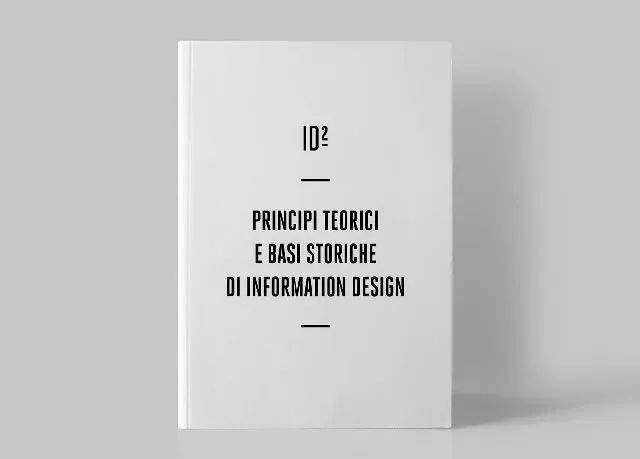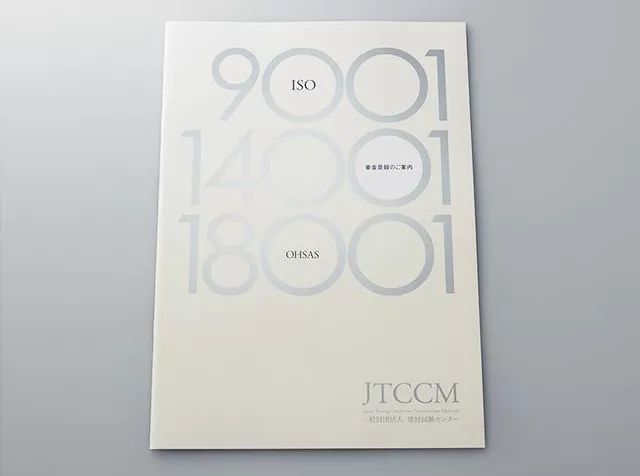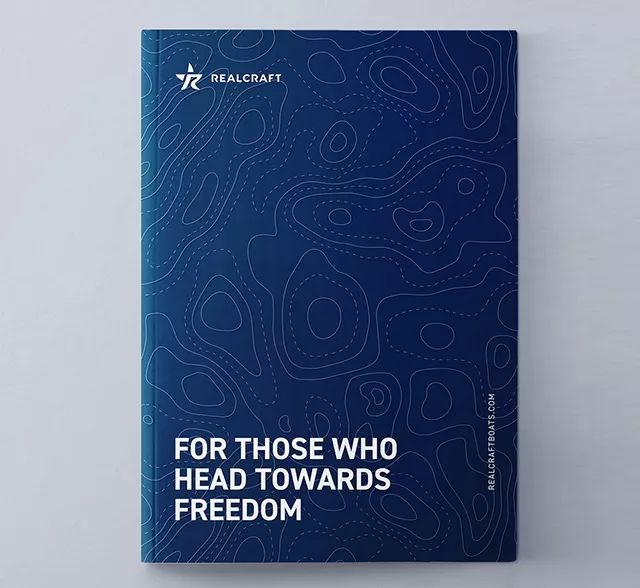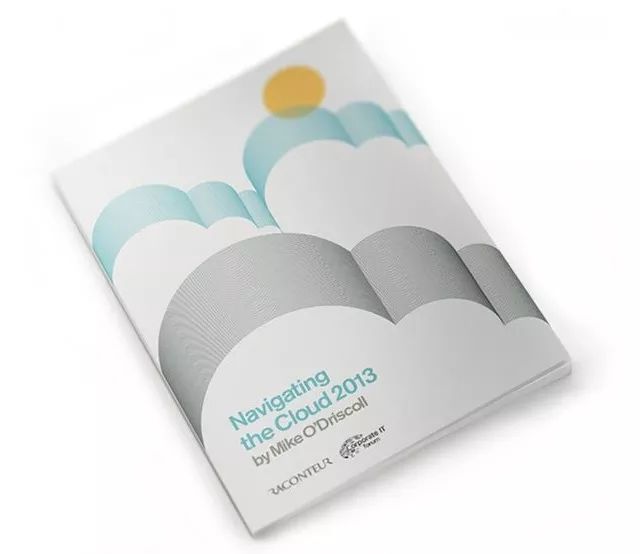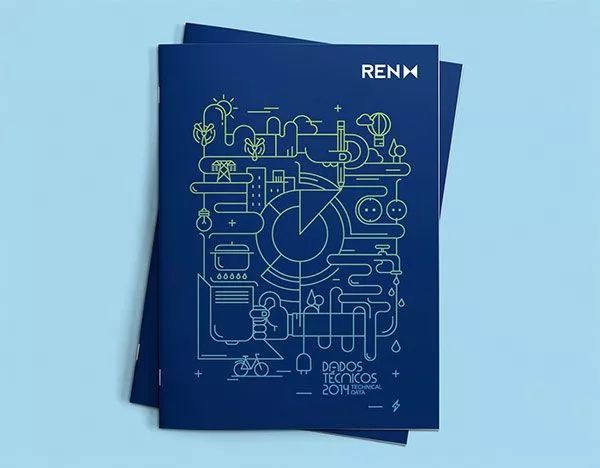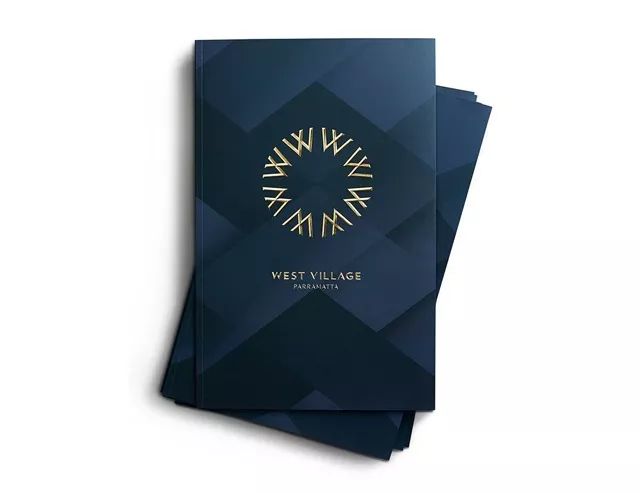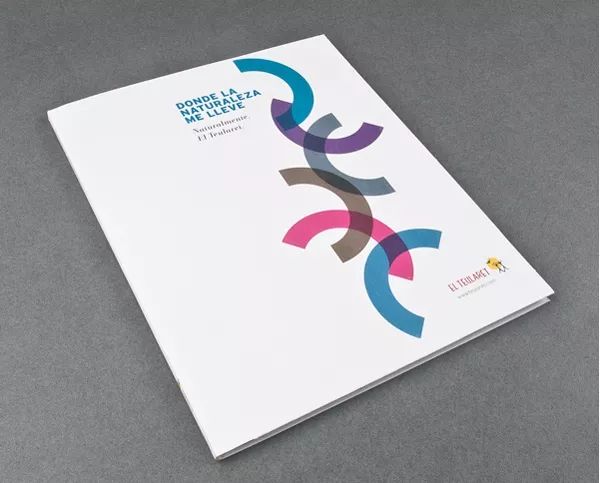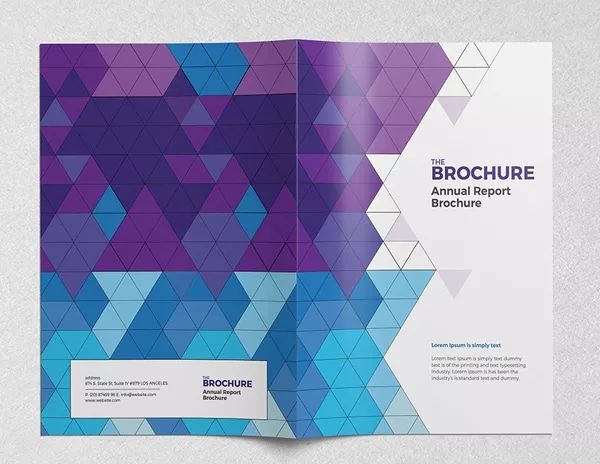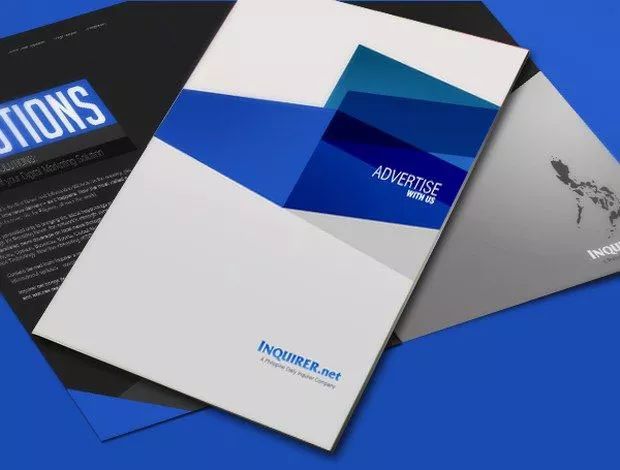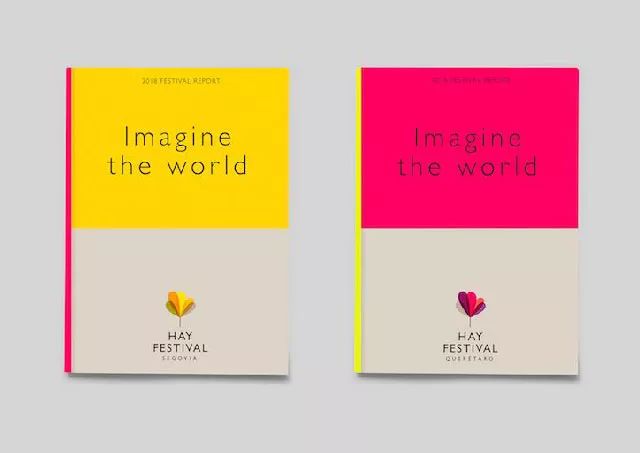
如何做好画册封面设计?6种常用形式分享
画册设计是平面设计师会经常遇到的工作,而画册的封面又是画册最为重要的部分,它起着概括画册内容、奠定画册调性、彰显画册品质,以及吸引读者的作用,而且画册设计对设计师的排版能力、构图能力、色彩搭配能力、审美、材质和工艺的运用都有不小的要求,值得深入学习和研究,所以葱爷决定专门写一篇文章,概括封面设计最常用的几种形式。
// 1.纯文字 //
即只用Logo、标题、公司名称等文字元素来设计封面,这类封面通常比较简洁,适合品牌画册、财务报表这种内容比较抽象、或者要求精装的画册设计。
这类封面设计的难度相对比较简单、主要依靠排版与字体的选择来创造设计感,排版时要注意文字的粗细对比、字号大小对比、字体对比、稀疏对比以及文字的颜色对比等等,为了增强设计感还可以加入少许直线来辅助排版。
提示:使用特种纸(如卡纸、花纹纸、牛皮纸等),或者添加一些简单的工艺(如激凸、磨砂、过UV、烫金烫银等),有助于加强纯文字封面的品质感。
// 2.文字加色块 //
纯文字的做法虽然简洁,但毕竟会有点单调、且视觉冲击力不足,这时我们可以考虑通过加增色块来进行丰富。色块除了可以增加视觉冲击力以外、还能增加设计感,而且可以通过大面积的色彩对比传达情感等。
不过增加的色块不宜过多,也不要过于分散,而是要以大色块为主,色块的轮廓常用简单的几何形。色块与文字的组合方式主要为文字位于色块内、文字位于色块外,以及文字与色块交叉。
提示:通过恰当的运用色块的颜色对比、虚实对比、大小对比、前后对比,可以有效增加版面的层次感。
// 3.文字加图形 //
如果想在封面设计上传达某个概念,或者想让设计更有内涵和细节,我们可以在封面上设计一个图形,把图形当成封面的主体,我这里所说的图形主要指适量图形。举个例子,如果我们要设计一本木地板品牌的产品画册,我们就可以设计一个年轮的图形来做封面。
在构图上常用的有主体居中、局部露出和平铺三种方式。
提示:图形的风格和形式要与画册整体的内容和设计风格相符。
// 4.文字加单图 //
在封面中使用与内容或品牌调性相匹配的摄影图片,也是很常见的一种方式,如果只使用一张图片,通常的处理方式是让图片占比较大的版面空间,图片的轮廓也是以简单的几何图形最为常见,当然,这是指图片为非去底图片的情况。
去底图片也会经常被用到封面设计中,它的灵活性更大,通常会配合色块一起使用。
文字与图片的排列方式也有三种,即文字排在图片上、文字与图片交叉、文字与图片分离三种形式。
提示:这类封面的图片质量是关键,要从图片的素材、构图、色彩、清晰度等方面严格筛选。
// 5.文字加多图 //
有些封面主题或画册内容很难用一张图片来概括,这时我们可以同时使用多张图片来设计封面,多张图片的处理方式主要有两种,即统一与对比,统一是指所有图片统一尺寸和色彩,并且采用有规律的方式排列。
而对比是指图片要在大小或者色彩上有鲜明的对比,形成主次关系和视觉层级。
提示:如果图片是从网络中获取的,一定要注意版权问题。
// 6.文字加图片加色块 //
这种形式算是一种混搭,它结合了前面提到的两种形式,其实文字加图片加色块的组合在广告设计和海报设计中也有广泛应用,它的优点在于变化丰富、设计感和视觉冲击力强。
图片与色块的组合方式主要有:图片位于色块上方、色块位于图片上方、色块叠印于图片上(降低色块透明度或采用正片叠底效果)、图片位于色块内、色块位于图片内、色块与图片交叉、色块与图片分离或相连并对齐排列。
提示:把图片处理成黑白模式再搭配色彩鲜艳的色块,通常能得到不错的效果,因为这么做既能避免颜色太花,而且能创造出强烈的对比效果。